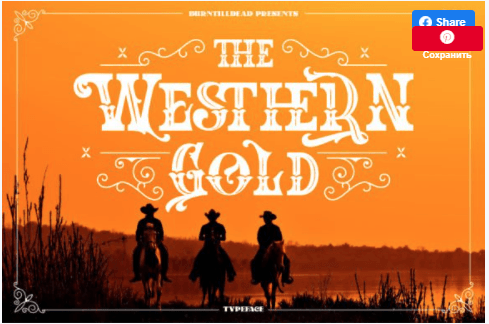
The Western Gold Font
Western Gold - это крутой шрифт с жирным шрифтом в западном стиле. Добавьте этот шрифт на свои этикетки, плакаты, брендинг и обратите внимание, как они выделяются! Western Gold закодирован в кодировке PUA, что означает, что вы можете легко получить доступ ко всем глифам и росчеркам!